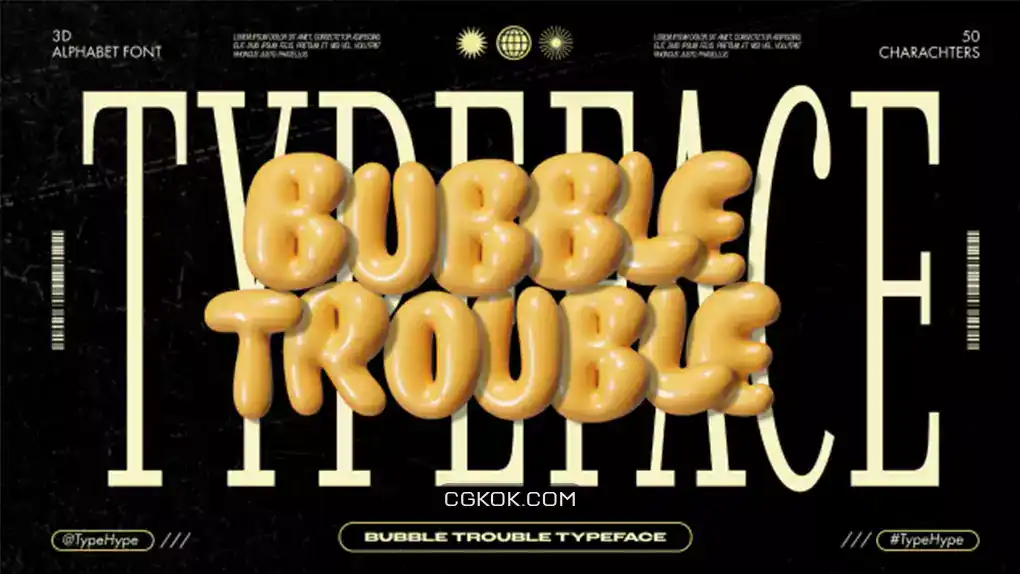
پروژه افترافکت انیمیشن متن حباب شکل : این پروژه یک قالب ویدیویی آماده با انیمیشن الفبا سه بعدی حباب شکل (50 کاراکتر) و 6 پس زمینه شیک میباشد. شما میتوانید رنگ، اندازه، سبک انیمیشن و غیره را ویرایش کنید. همچنین میتوانید پس زمینه را به گونه ای تنظیم کنید که با سبک شما مطابقت داشته باشد. این محصول قابلیت اجرا و سازگاری کامل با نرم افزار افترافکت CC 2020 و ورژن های بالاتر را دارد. این پروژه دارای رزولوشن 2160 × 3840 است و کار با آن نیاز به پلاگین ندارد.